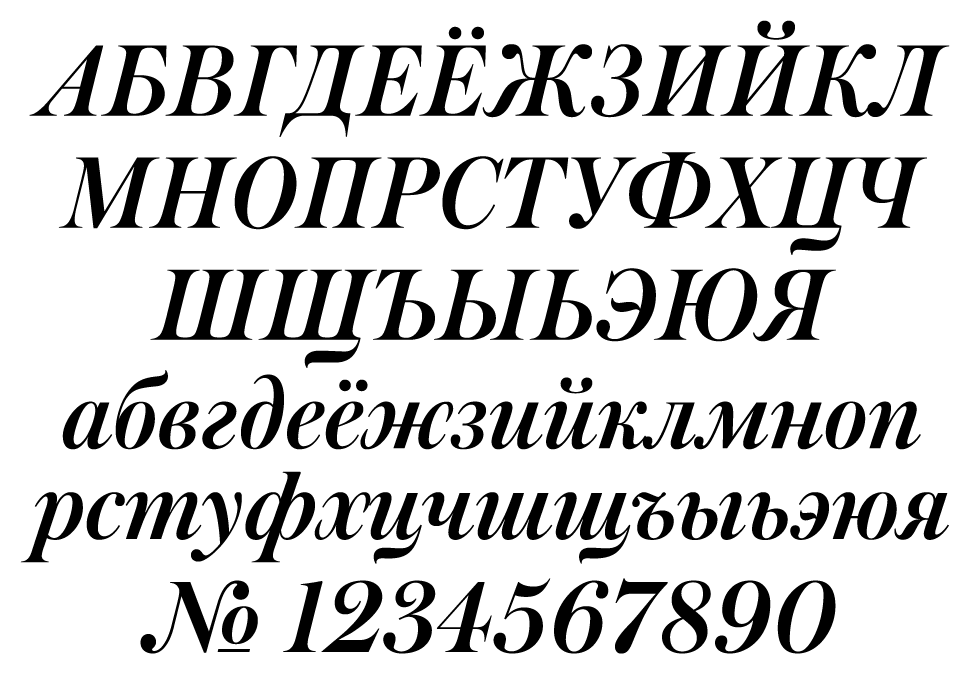
Курсивный шрифт: шрифты, которые мы рекомендуем для вашего дизайна
Когда у вас есть работа, опубликовать книгу, представить проект, выбор правильного шрифта может быть гораздо важнее, чем вы думаете. В зависимости от цели, которую вы хотите достичь с помощью этой задачи, вы можете выбрать другую букву, другой стиль. Фактически, неправильный выбор помешает людям подключиться к передаваемому сообщению. И часто мы игнорируем использование разных букв, например курсив и их шрифты.
Чтобы помочь вам понять что такое курсив и даст вам варианты шрифтов этого типа письма, прежде чем вы должны знать его немного больше. И этим мы займемся дальше.
Что такое курсив
Курсив также известен как рукописный или буквенный шрифт. Это способ письма, который напоминает то, как вы пишете на самом деле, с наклоном букв, с конкатенацией букв или без нее… Однако шрифты с наклоном вправо (курсивные буквы) также называются курсивными буквами. курсив”).
Этот шрифт существует уже сотни лет. На самом деле это рукописное письмо – то, которое стали использовать для написания стихов, книг и т. д. так как в прошлом люди «копировали» тексты, чтобы составлять из них книги, и все они были написаны этой буквой.
Однако тот, который больше всего похож на тот, который мы сейчас используем, пришел из XNUMX века, где мы можем видеть его образцы на пергаментах, написанных от руки пером и чернилами.
Вскоре после этого британская аристократия решила выгравировать этот шрифт на медных пластинах, чтобы его можно было использовать для печати, и эти завитки стали украшать многие публикации.
Курсив: шрифты и характеристики
Сегодня курсив и его шрифты характеризуются имеют недостатки, которые сами по себе делают их уникальными, стиль, как если бы вы писали ручкой или кистью, и загружен, в большей или меньшей степени, завитушками.
Многие из них легко читаются, хотя есть и другие, которые из-за наклона и способа написания нечитаемы, особенно если не используется крупный шрифт.
Для чего использовать курсив?
Независимо от того, что вы можете использовать курсив в разных шрифтахКак бесплатные, так и платные, правда в том, что этот тип письма используется для очень определенных целей. Например:
- Чтобы поставить иностранные слова: обычно, когда вы пишете предложение, в котором есть слово, написанное на другом языке (французском, английском, итальянском …) в испанском тексте, это слово выделяется курсивом.
- Размещение псевдонимов или слов, которые являются псевдонимами, а не настоящими именами.
- Что касается названий, будь то фильмы, книги и т. Д.
- Для названий видов – это научное название животного или растения.
- Для собственных названий транспортных средств (Orient Express, Renfe, Alsa …).
- Если вы имеете в виду названия метеорологических явлений (Филомена, Катрина …).
- Чтобы выразить иронию.
Хотя это норма для курсива и использования его шрифтов, правда в том, что есть «особые» ситуации, в которых вы также можете его использовать. Например, это может быть для формальных ситуаций, таких как написание свадебного приглашения, романтического письма или создание заголовка и заголовков, привлекающих внимание, будь то в журнале, на работе, в книге…
На веб-страницах или на предметах, связанных с дизайном, также можно использовать курсив. Проблема в том, что этот шрифт непросто понять с первого взгляда И, хотя он визуально красив, он может затруднить прохождение сообщения, поэтому многие предпочитают оставлять эти типы шрифтов для «декоративных».
Курсивный шрифт: шрифты, которые вы можете использовать
Ниже мы сделали компиляция некоторых курсивных шрифтов, которые вы можете использовать в случае необходимости. Конечно, помните, что злоупотреблять ими не стоит, поскольку, если дизайн, который вы собираетесь поставить, будет перегружен, сам шрифт может оказаться слишком большим для окончательного набора.
Вот наши рекомендации:
Танцевальный сценарий
Выделенный курсивом, это один из самых красивых шрифтов, которые вы можете использовать. Его преимущество заключается в том, что хотя буквы прикреплены, и в нем есть некоторый штрих, он легко читается и хорошо понимается, чтобы вы могли разместить его в блогах, публикациях и т. д.
Конечно, мы говорим не очень формально, но в рамках неформального курсивного шрифта. Тем не менее, это может быть красиво для ваших проектов, особенно если вы хотите, чтобы он выделялся из-за того, насколько он выглядит смелым.
Allura
Allura – еще один курсивный шрифт, который вы можете использовать.
Он четче, как если бы вы писали от руки, плюс в нем больше изюминок. Тем не менее, он все еще довольно удобочитаемый. Единственное, что иногда вам придется размер больше обычного, так что он хорошо понятен.
Чтобы узнать, какие другие параметры текста Unicode доступны, посетите этот демонстрационный сайт.
3 Г-н фон Мюллерхофф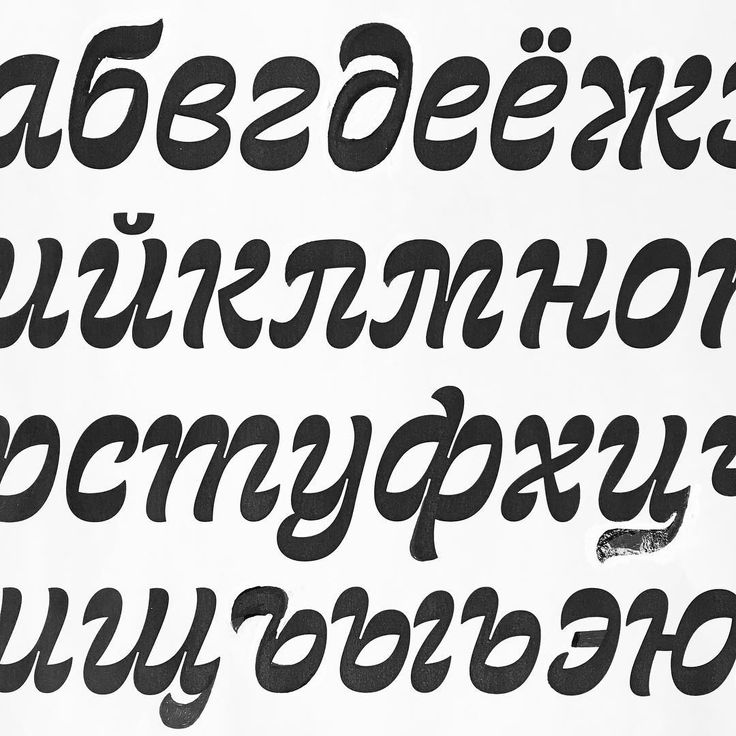